책장을 넘기며 손끝에 닿는 종이의 결, 그리고 잉크와 섞인 시간의 향기는 언제나 깊었다. 나는 어렸을 때부터 익숙하게 맡아왔던 그 조용한 종이 냄새가 좋았다. 마치 오래된 편지를 꺼낼 때 느껴지는 기억과 동일했다고나 할까. 그곳에 한 줄씩 써 내려간 하나의 미학적 구조는 나의 마음을 울리기도, 웃기기도 했다. 그래서 처음 디지털 포엠을 접했을 때 그것은 복잡하고 낯설게만 다가왔다. 내가 펼치기만 하면 움직이지 않고 가만히 고정된 글자가 어느 순간 나의 동공을 가지고 놀았다. 마치 그곳은 작은 무대 같았다. 공간 전체를 장악하는 매체가 선뜻 와닿지 않으면서도 이상하게 끌리기 시작했다. 화면 위에서 깜빡이고 움직이며 시간에 따라 의미가 달라지는 디지털 포엠이 과연 우리의 문학적 소양과 연관이 있을까?
과거의 시는 고요하게 글자를 따라간다. 우리의 마음과 머릿속에 스며드는 순간들은 언제나 차분하고 끝이 보이지 않는 풍성한 바닷속처럼 깊었다. 언제나 일정하게 배치된 문장을 읽으며 선형적으로 나의 시선은 움직였다. 시의 구조(행과 연)는 독자의 시선이 직선적이고 고정된 흐름 속에서 사유하게끔 유도했다.
이와 달리, 새롭게 떠오르고 있는 디지털 포엠은 디지털 매체상에서 창작, 유통, 수용되는 모든 형식의 디지털 시를 말한다. 텍스트가 살아있는 듯한 움직임, 이미지, 소리와 영상 등 멀티미디어 요소의 결합을 통해 우리의 시적 경험을 만들어내는 장치이다. 디지털 포엠을 처음 접한 나는, 화면에 스치듯 나타났다가, 언제 사라졌냐는 듯이 화면 속에 푹 주저앉아 있는 글자들을 보고 꽃에 앉은 나비가 생각이 났다. 나비는 색깔과 향기에 예민해서 선명한 색과 향이 강한 꽃을 찾는다. 마치 이것처럼 사람의 눈도 본능적으로 강렬하고 대비가 큰 이미지에 시선이 먼저 향한다. 내가 평소에 알고 있는 시와는 다른 감각이라, 처음에는 글자의 출현과 소멸을 가볍게만 스치듯 읽었다.
디지털 포엠에 관한 수업을 듣고 또 내가 직접 만들어 보는 시간을 보내며 디지털 포엠을 곱씹어보고, 깊이 사유하는 시간을 가졌다. 그 순간 글자가 전혀 없는 여백까지 감지하고 있는 나를 발견했다.
뭉게뭉게 퍼져 있는 글자, 한 곳에 우르르 모여 있어 여백과 대비감을 주는 공간에 오래 머물다 보니 나의 마음과 사유, 감각을 강하게 끌어당겼다. 또한 실제로 움직이기도, 소리 나기도, 나의 시선을 통해 달라지는 메시지들이 마치 나를 강하게 붙잡고 있는 중력과 같다고 해야 할까. 시를 읽으며 처음 느껴보는 기분이었다.
나는 새로운 시적 장르를 배우며 직접 디지털 포엠 작품들을 창작했다. 아래는 그 가운데 하나인 비주얼 디포엠 <빛은 스며들 때 빛난다>이다.
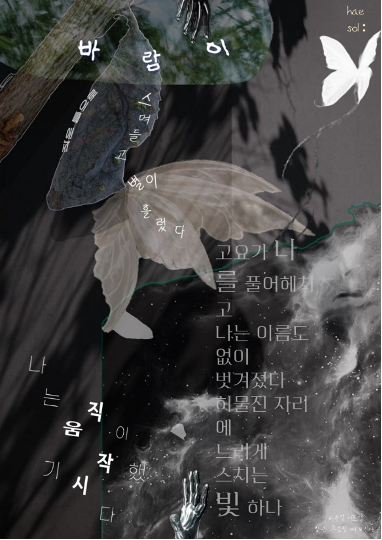
실제로 <빛은 스며들 때 빛난다>을 보면 글자가 한 군데에 밀집해 있는 모습을 볼 수 있다. 화면 속 텍스트의 배치를 보면 중심과 여백이 만들어져 있다. 글자가 빽빽하게 모인 부분은 압도적인 무게를 띠며 우리의 감정과 생각의 깊이를 만들었고, 자연스레 시선이 가도록 만든다. 이는 단순한 시각 효과가 아닌, 공간 전체를 점유하며 심리적 압력을 만들어 낸다. 이는 언어가 단순히 의미 전달을 넘어 물질적이고 감각적인 힘을 가진다는 사실을 새롭게 인식하게 된다.
이 밀집은 시의 정서적 무게로 이어진다. 빽빽하게 쌓인 단어들은 독자에게 몰입을 요구하며 “자연스럽게 여기가 핵심이다”라는 감각을 형성한다. 반대로 주변에 넓게 펼쳐진 여백은 그 무게를 더 돋보이게 한다. 여백과 대비되는 밀도의 차이가 독자는 의도하지 않아도 그 균형 속에서 의미의 구조를 점점 체감한다. 즉, 우리의 시선을 오랫동안 머무르게 하는 글자의 밀도는 단순한 시각적 배열이 아니라 정서적 중심을 조직하는 하나의 장치이다. 이러한 정지의 순간과 시간의 응축은 독자의 시적 결절을 경험케 하고, 하나의 중심 부분에서 벗어나 즉, 단일 중심에서 다중 중심이 될 수 있다는 새로운 깨달음을 얻는다. 이러한 움직임은 익숙한 지각을 무너뜨리고, 낯선 충격 속에서 우리는 새로운 감정과 깨달음을 얻게 된다.
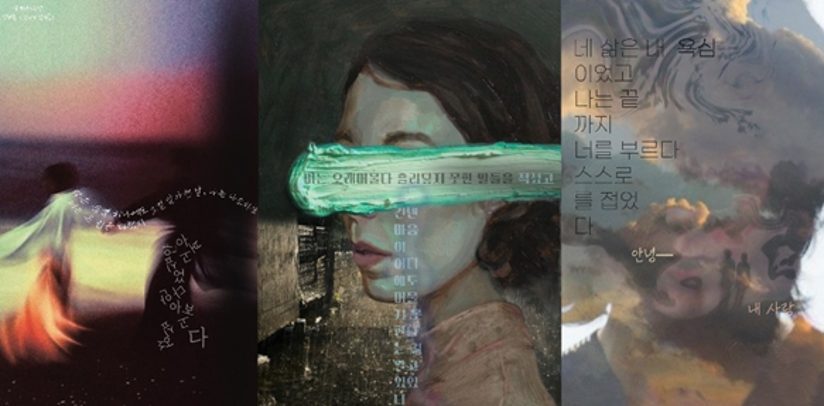
두 번째 작품은 디지털 포엠의 하위 갈래인 삼면화 디포엠, <헛되지 않기를>이다. 이 작품을 보면 다양한 특이점들이 분포되어 있다는 사실을 알 수 있다. 예를 들어 텍스트의 강렬한 색깔, 불균형한 배치, 이상 현상, 글자의 배열, 사라지다가도 다시 나타나는 것들. 이것을 비유해 보자면 삼각형의 “꼭짓점”, 저기압과 고기압의 “중심점”들로 우리는 이것들이 어떻게 구성되고 있느냐에 따라 특이점이 달라지고, 어떻게 해석할 것인지 알 수 있다. 결국 시 속에서 갑자기 눈길을 확 끄는 순간은 원래부터 가지고 있던 독특한 성격을 구성하고, 이 성격은 특이점을 다시 해석하게 만드는 순환 관계를 만든다. 디지털 포엠은 독자에게 편한 독서가 아닌, 낯선 체험을 요구한다.
이처럼 디지털 포엠은 정지, 밀도, 여백, 그리고 불시에 찾아오는 순간들을 통해 우리의 감각을 깨운다. 빠르게 이어지던 문장이 갑자기 멈출 때, 예상치 못한 색이나 배열, 리듬이 우리의 안정감을 깨트릴 때, 밀도와 여백으로 시각적 무게와 사유의 정지 점을 통해 각자의 새로운 체험의 문이 열리게 해준다. 결국 디지털 포엠은 단순히 읽는 텍스트가 아닌, 우리의 감각을 확장하는 예술임을 다시 확인하게 한다. 자연스레 시를 읽는 독자도 해석을 위해 존재하는 것이 아닌, 감각적 체험의 참여자가 되는 것이다.
우리는 더 이상 텍스트만 읽고 보지 않는다. SNS와 온라인 커뮤니티를 보아도 지금은 우리가 보고, 듣고, 넘기고 반응하는 방식으로 콘텐츠를 경험하고 있다. 책보다 화면, 스크롤, 영상에 익숙한 것과 같이 시도 새로운 감각 구조 안에서 확장된 감각적 예술로 변화될 필요가 있다.
디지털 포엠은 종이 시집을 대체하지 않는다. 종이는 여전히 인간 사유의 고요한 문을 열어준다. 하지만 중요한 것은 매체의 구분이 아니라, 그 매체가 어떻게 우리의 감각을 흔들고 사유의 길을 확장하는지에 대한 문제이다. 나는 이제 시를 읽을 때 시어의 의미만을 좇지 않고, 순간적으로 보는 감각성을 더 중요시하게 됐다. 감각을 키워서 순식간에 발동하는 의미들, 나의 감정과 감각을 발견한 후에 텍스트를 볼 수도, 또는 이런 개념들을 동원해서 해석하고 감상할 수 있겠다. 디지털 시대의 디지털 포엠은 고정된 언어를 넘어, 반복과 특정 공간, 정지와 낯섦을 통해 우리의 감각을 확장하고, 다르게 쓰이고, 다르게 읽히더라도 디지털 포엠을 포함한 모든 시의 장르는 여전히 우리의 정서를 자극해 몸과 마음으로 생생하게 느끼게 만들어 준다.